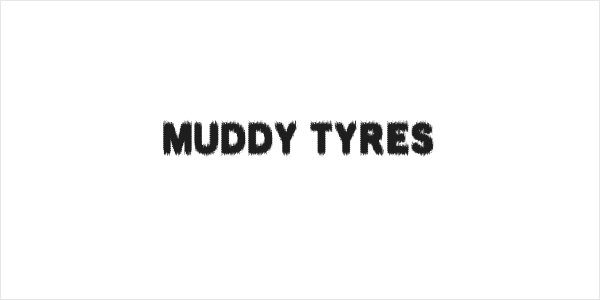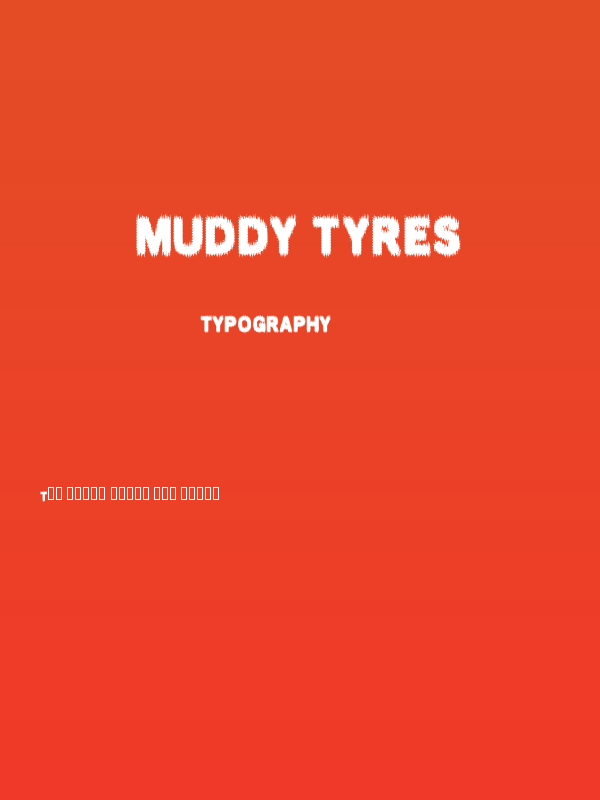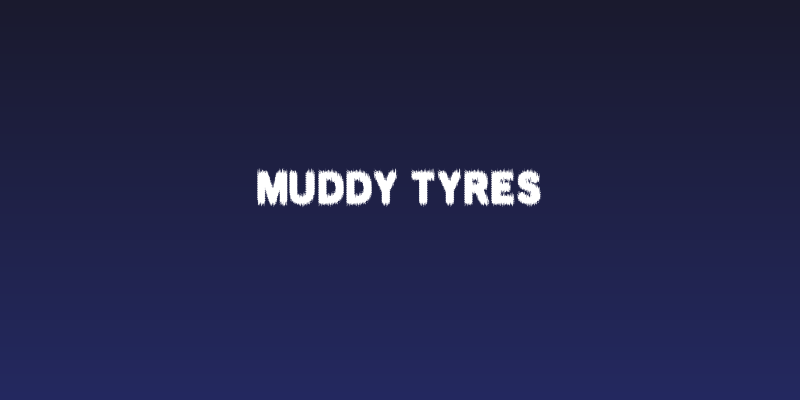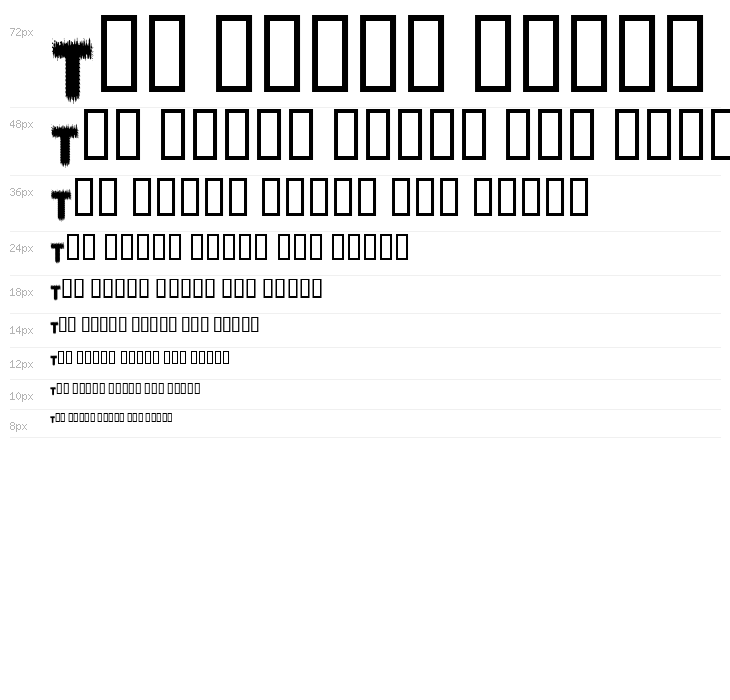
MUDDY TYRES Font
| Progetti proposti | Ideal for outdoor adventure branding, extreme sports event posters, or any design needing a bold, gritty aesthetic. |